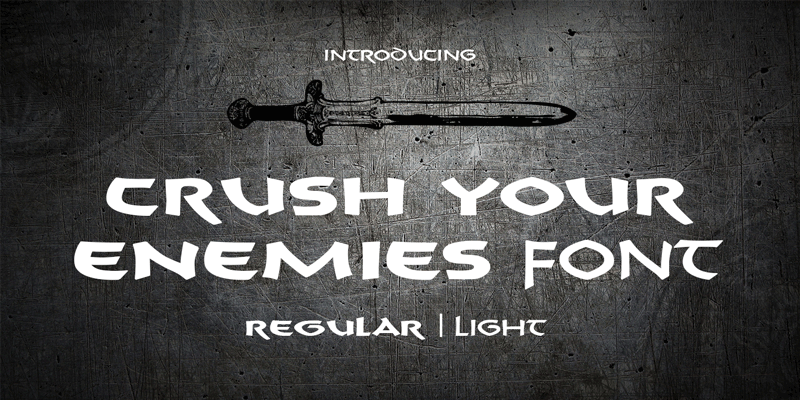
Crush Your Enemies Font
Fonte baseada nos créditos de abertura do filme Conan the Barbarian de 1982. É a recriação mais fiel e segue de perto o desenho original. Esta é a versão light, que é inédita no mercado de fontes.